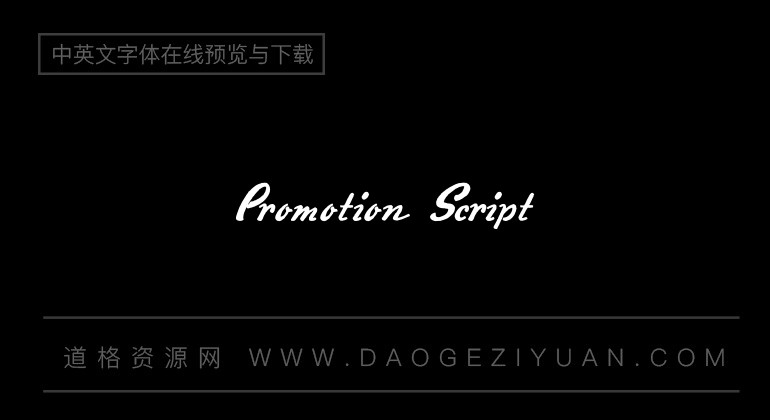
Promotion Script
Promotion Script 是一种优美、流畅的手写风格字体,常用于广告、海报、卡片等设计中。它的特点是字母之间的连续性,使得整段文字具有一定的流动感和艺术感。这种字体常用于商业或文艺类设计中,可以很好地突出文本内容的重点和创意,吸引读者的眼球。
Promotion Script是一款非常不错的手写艺术字体,具有很好的视觉感,适合于文化类的宣传设计、商业类品牌的广告和产品包装设计以及个性化文字排版等较多场景。